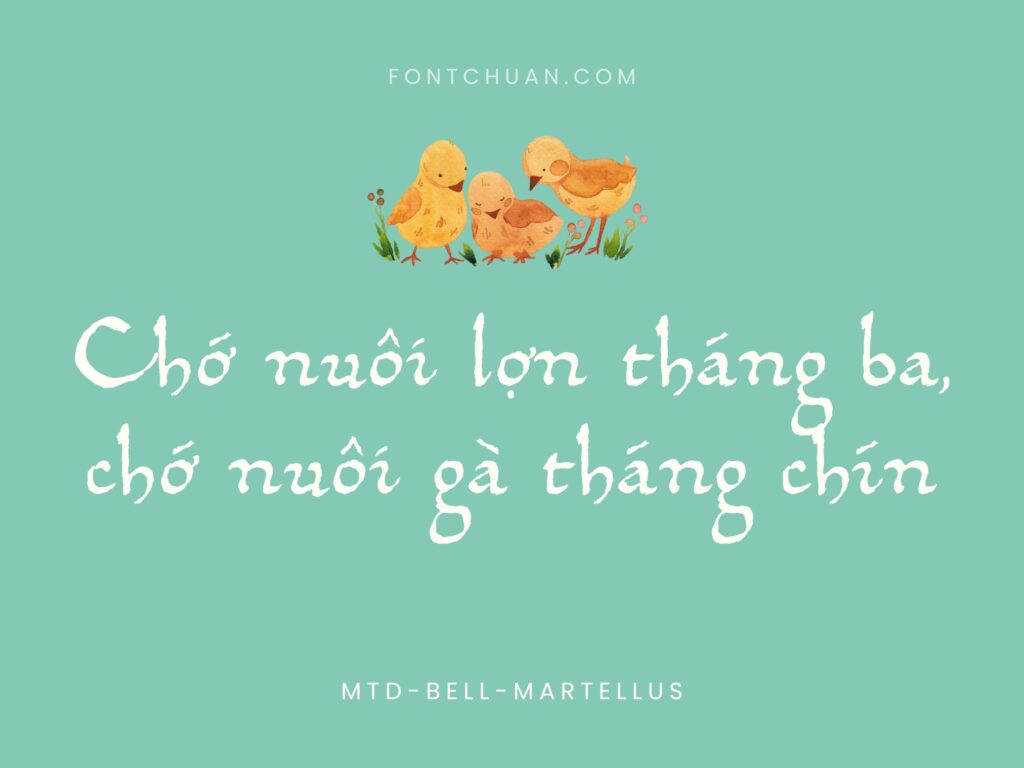
Font MTD Bell Martellus Việt Hóa
Font MTD Bell Martellus là một kiểu chữ viết tay cổ điển, được thiết kế bởi Bill Moran và đã được Việt hóa bởi Mộc Hạ. Font này hỗ trợ đầy đủ tiếng Việt cùng hơn 90 ngôn ngữ khác, mở rộng khả năng ứng dụng trong các thiết kế đa ngôn ngữ. Đây là một trong những phông chữ được cộng đồng thiết kế đánh giá cao và sử dụng trong nhiều dự án sáng tạo, đáp ứng nhu cầu đa dạng của người dùng.
MTD Bell Martellus nổi bật với các đường nét mang phong cách thư pháp cổ điển, tạo cảm giác lịch sử và nghệ thuật. Font rất phù hợp cho các thiết kế liên quan đến văn hóa, lịch sử, thiệp mời, bao bì sản phẩm và các ấn phẩm đòi hỏi sự tinh tế và độc đáo. Các ngành nghề phù hợp bao gồm quảng cáo, giáo dục, công nghệ, thiệp cưới và ảnh cưới. Font này cũng lý tưởng cho các sự kiện như Tết, Giáng sinh, Valentine và các lễ hội khác.